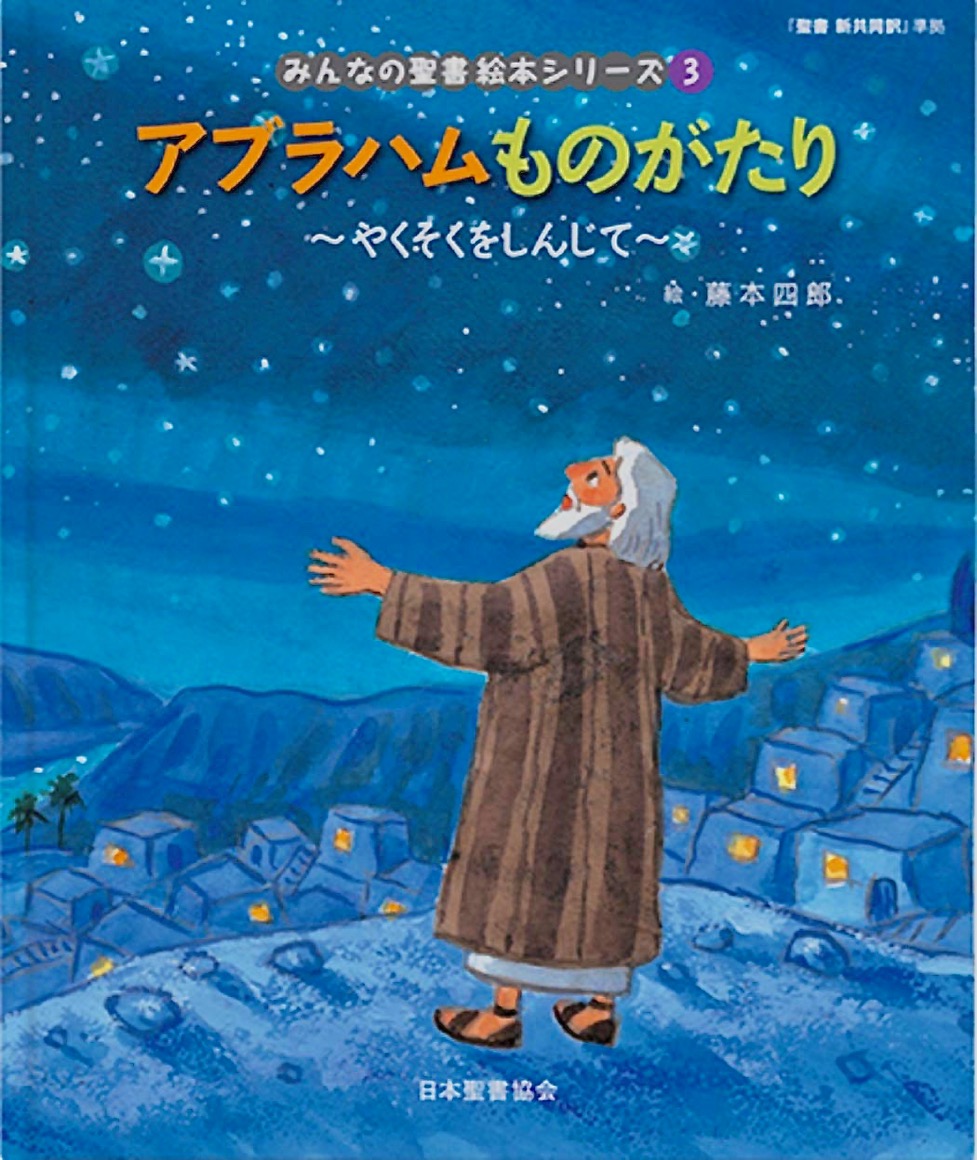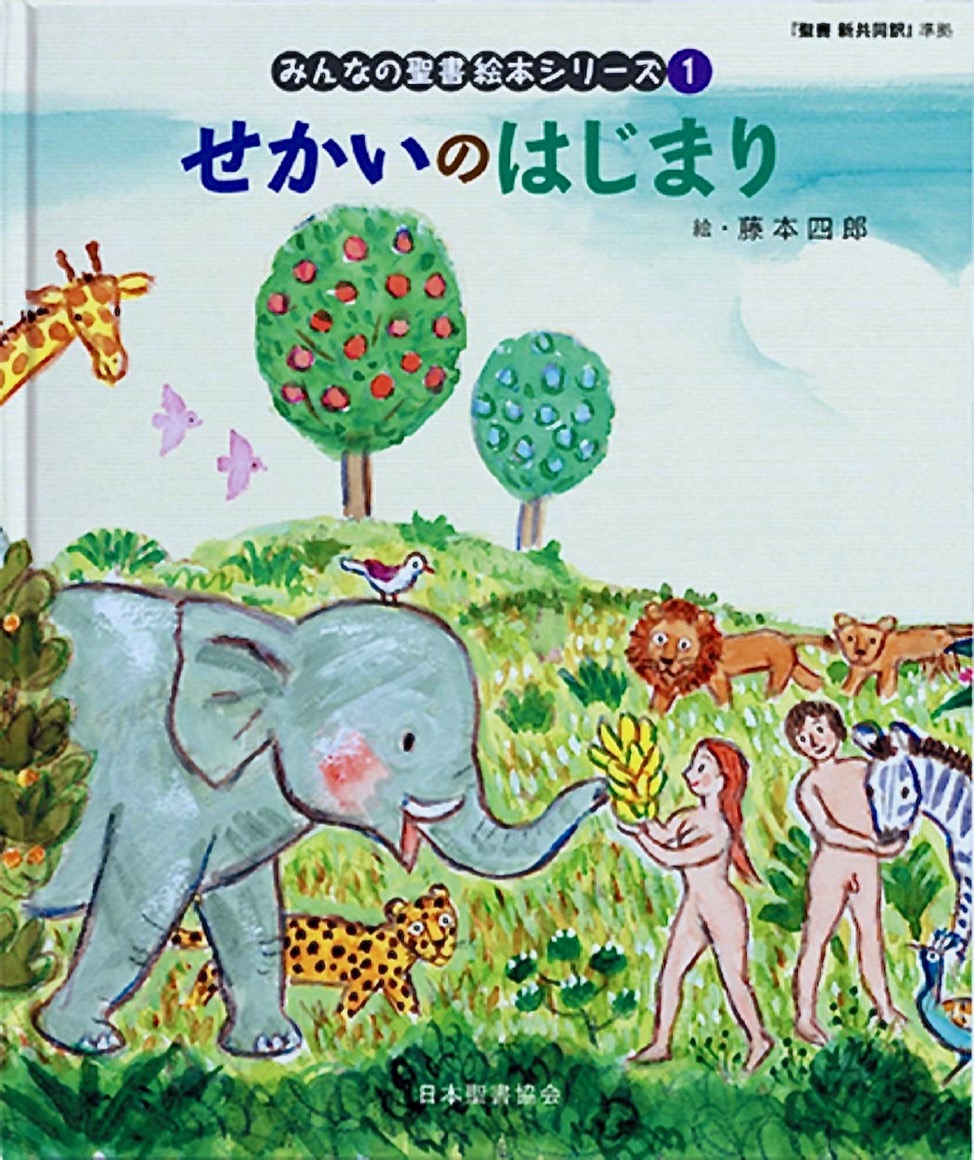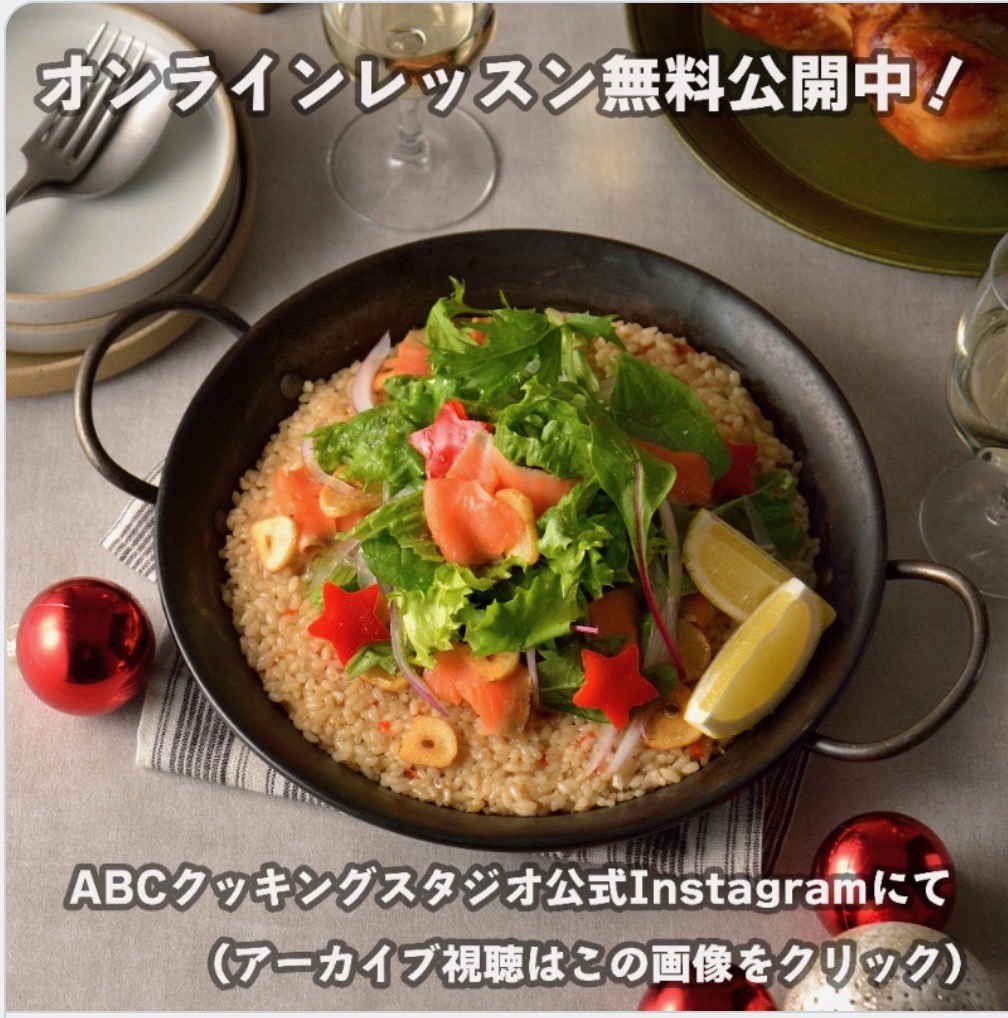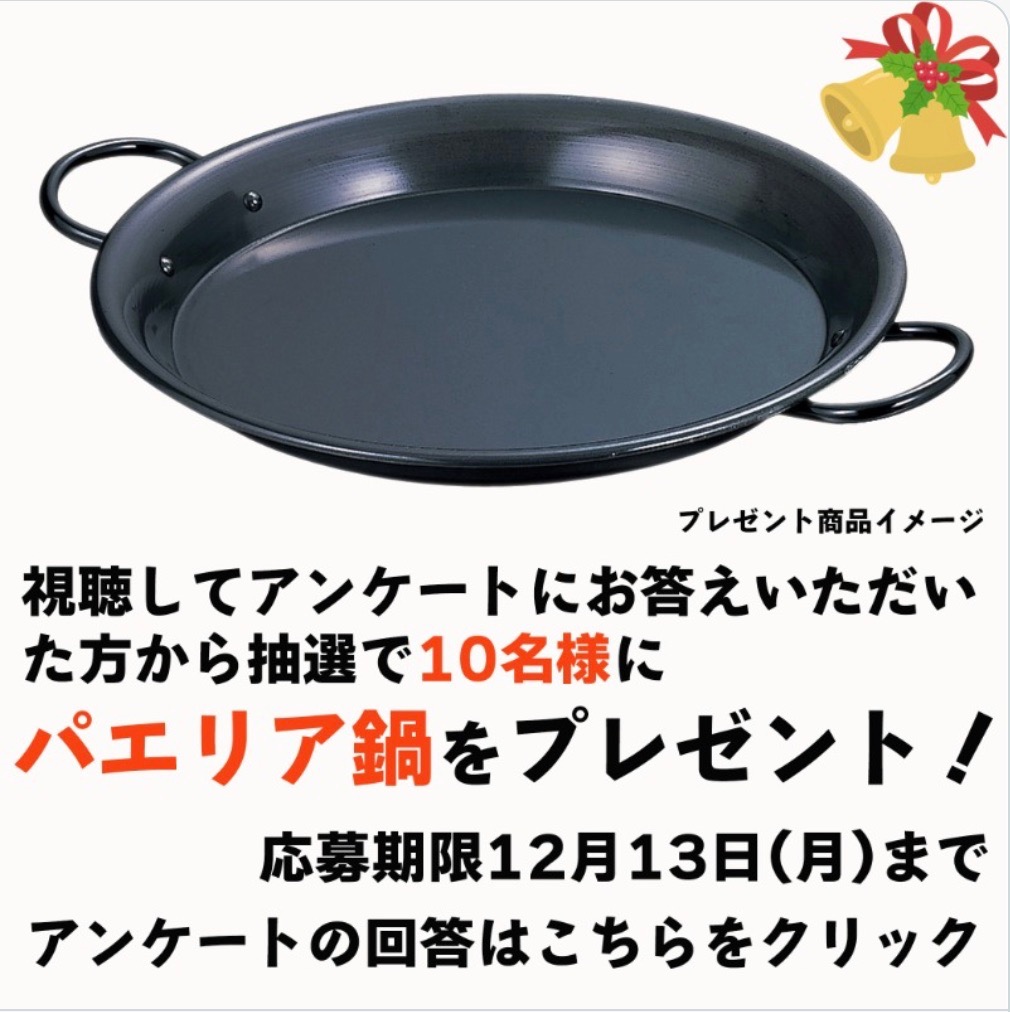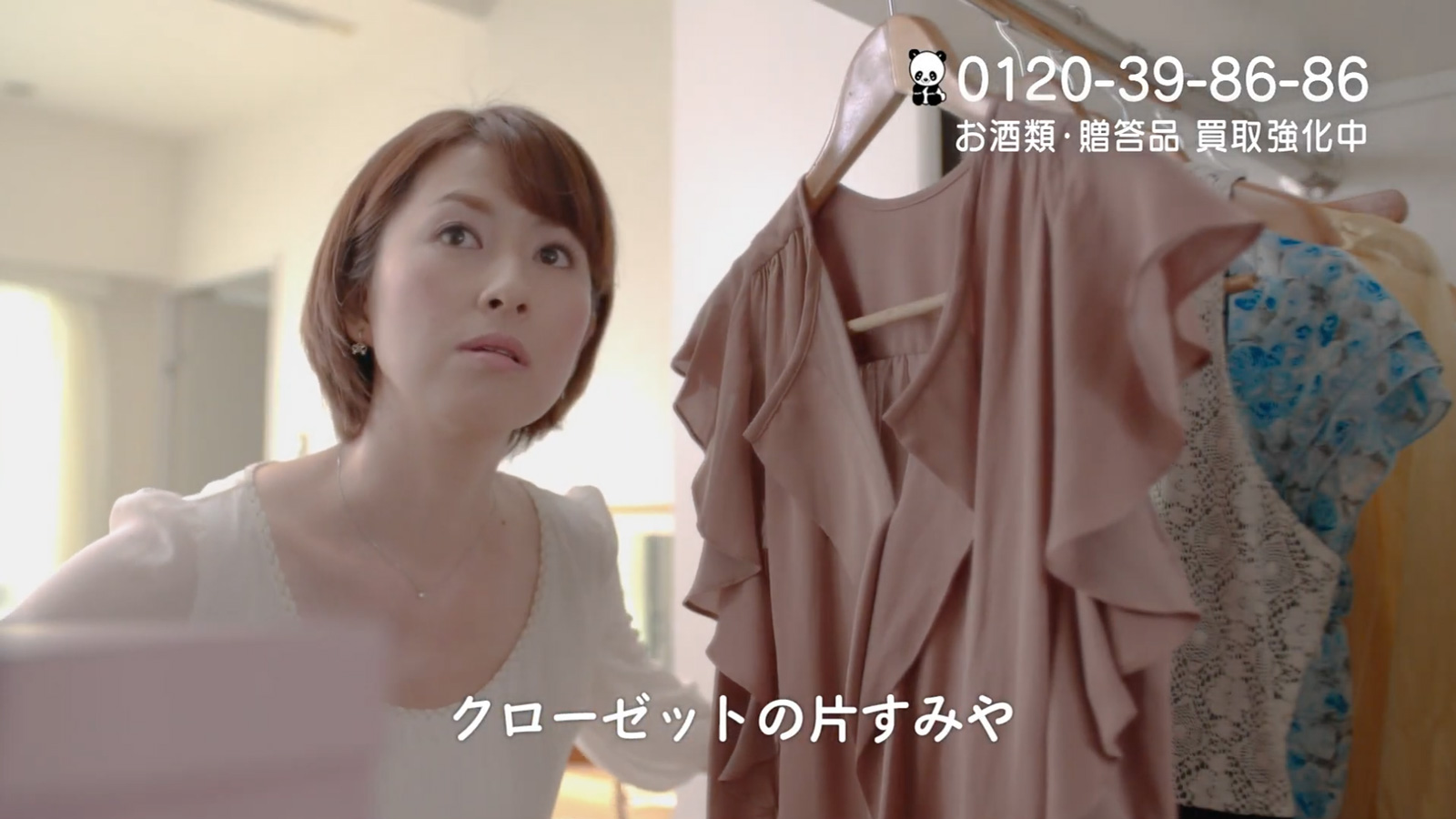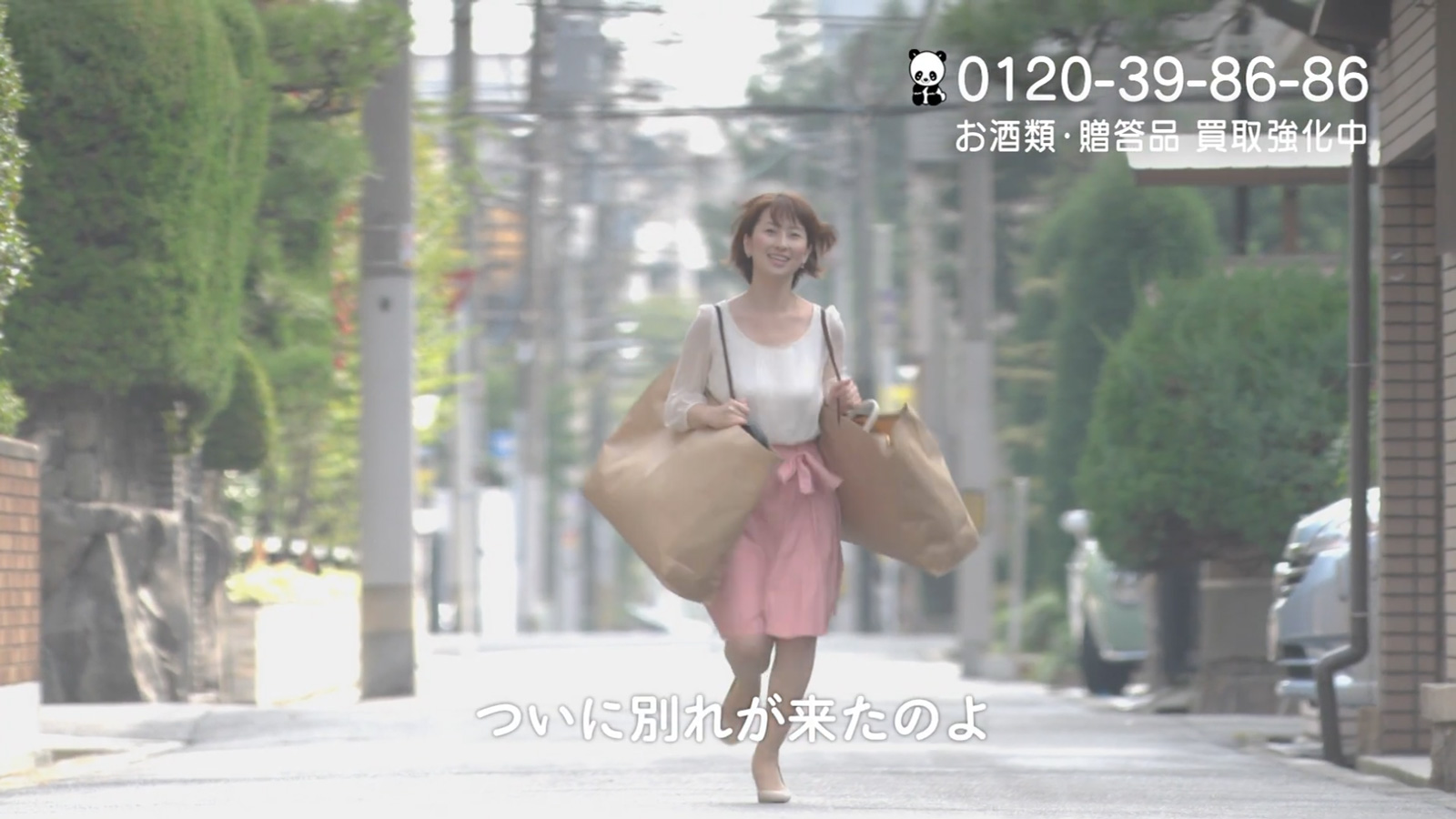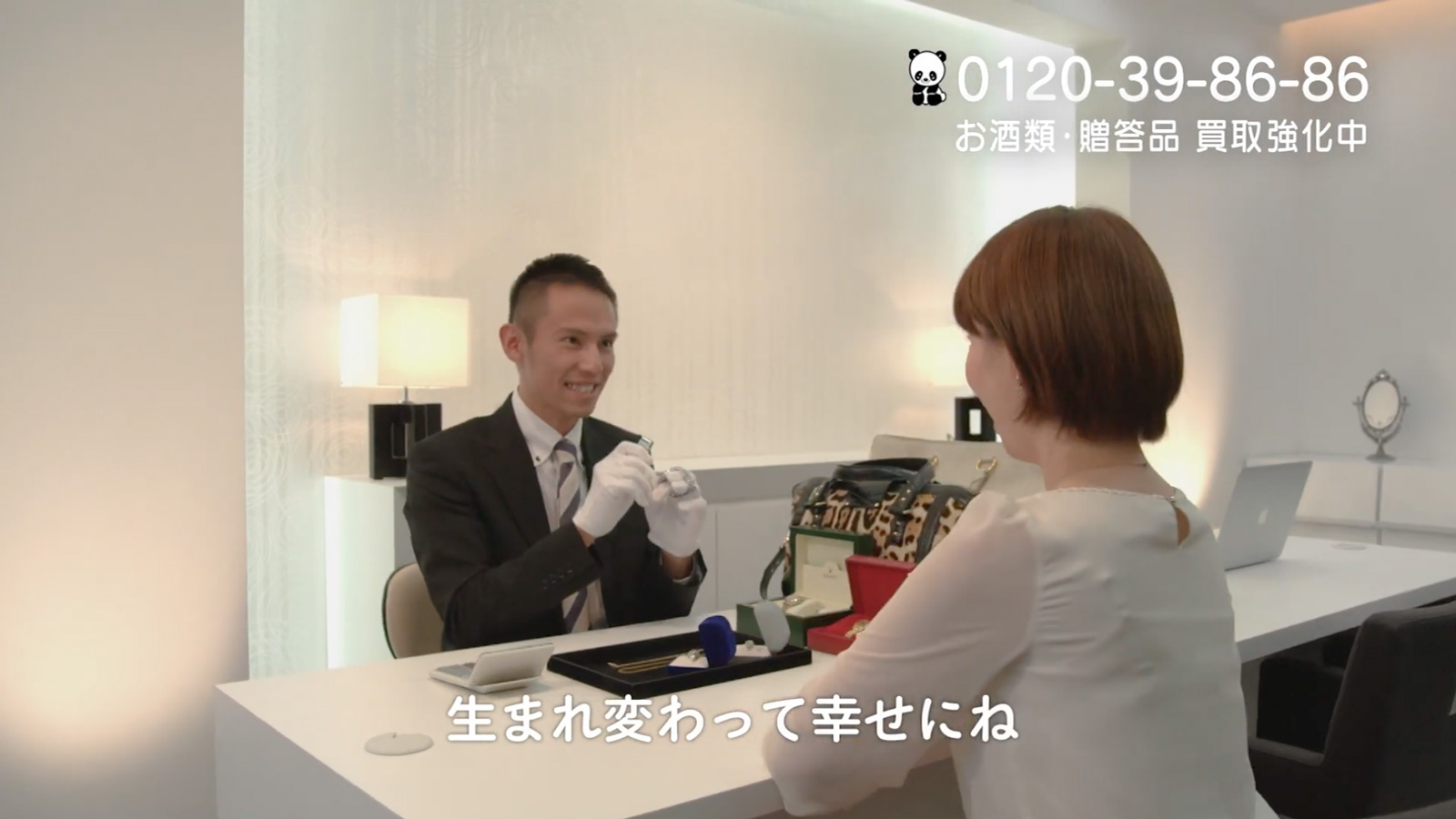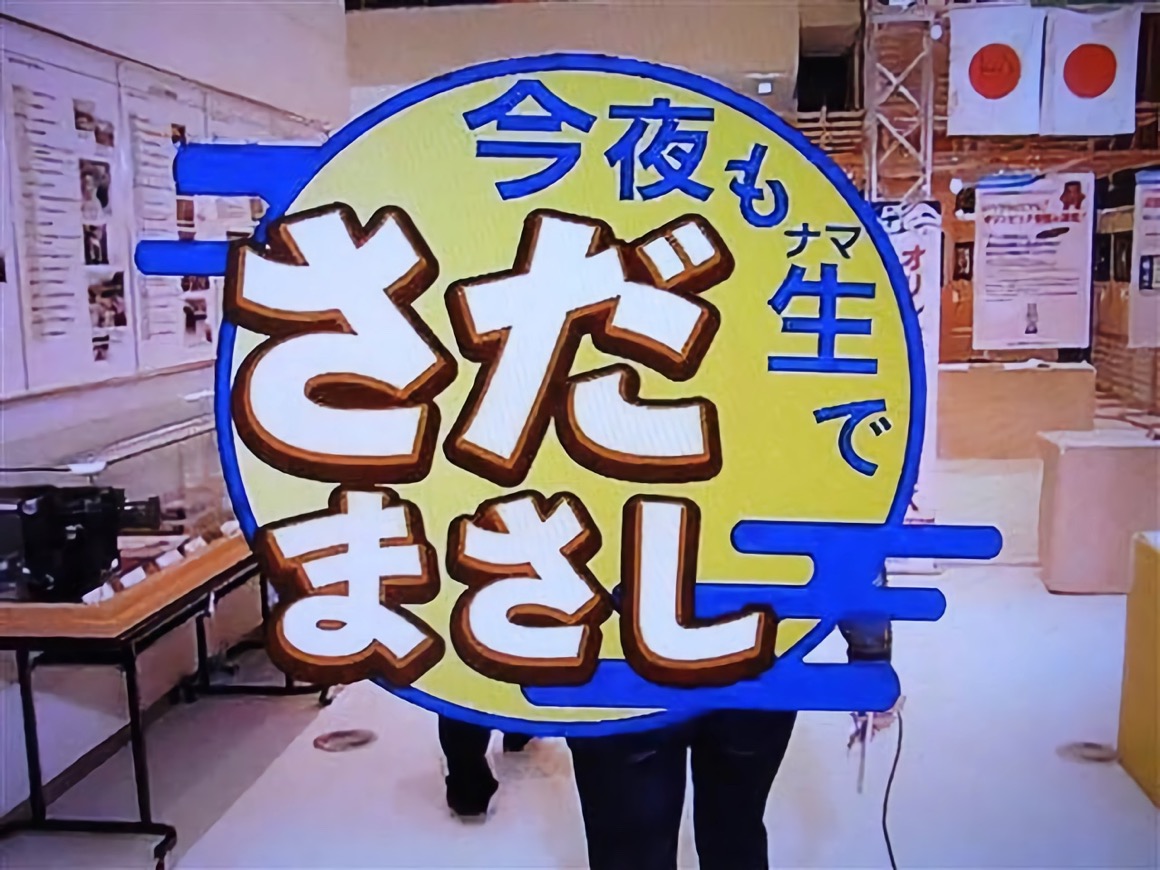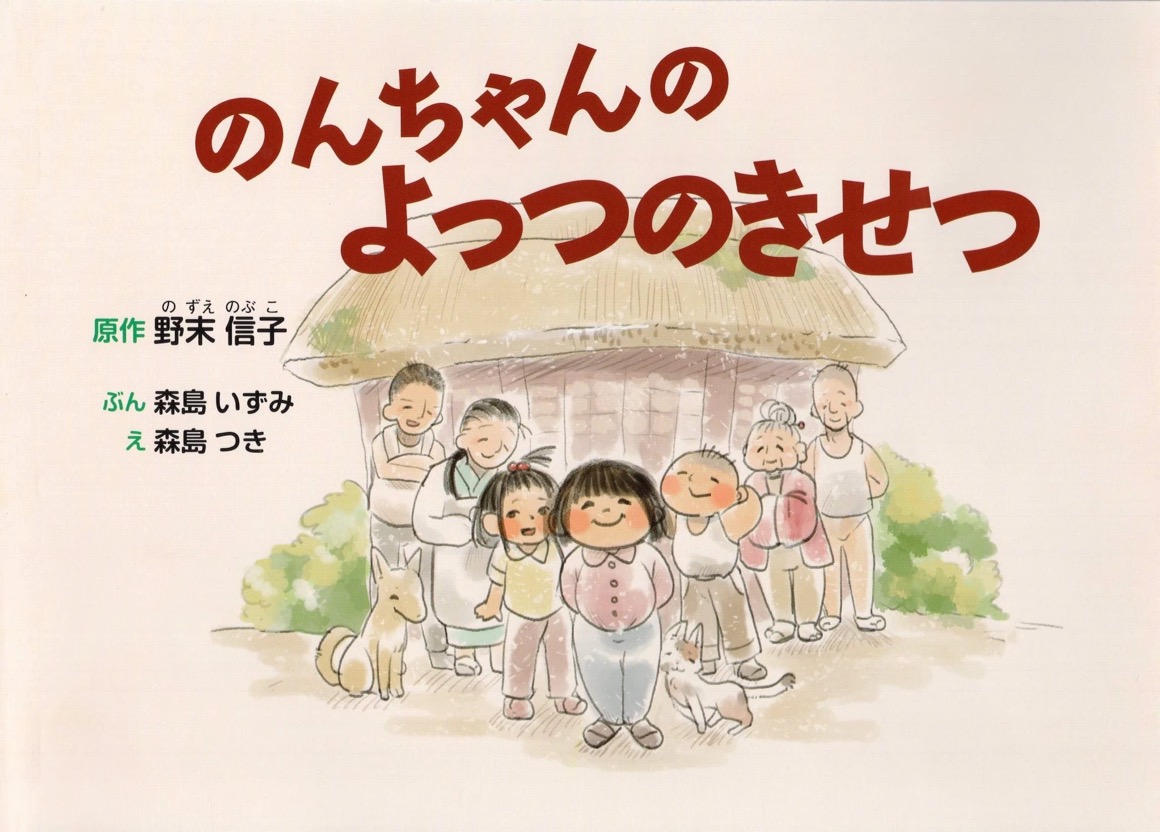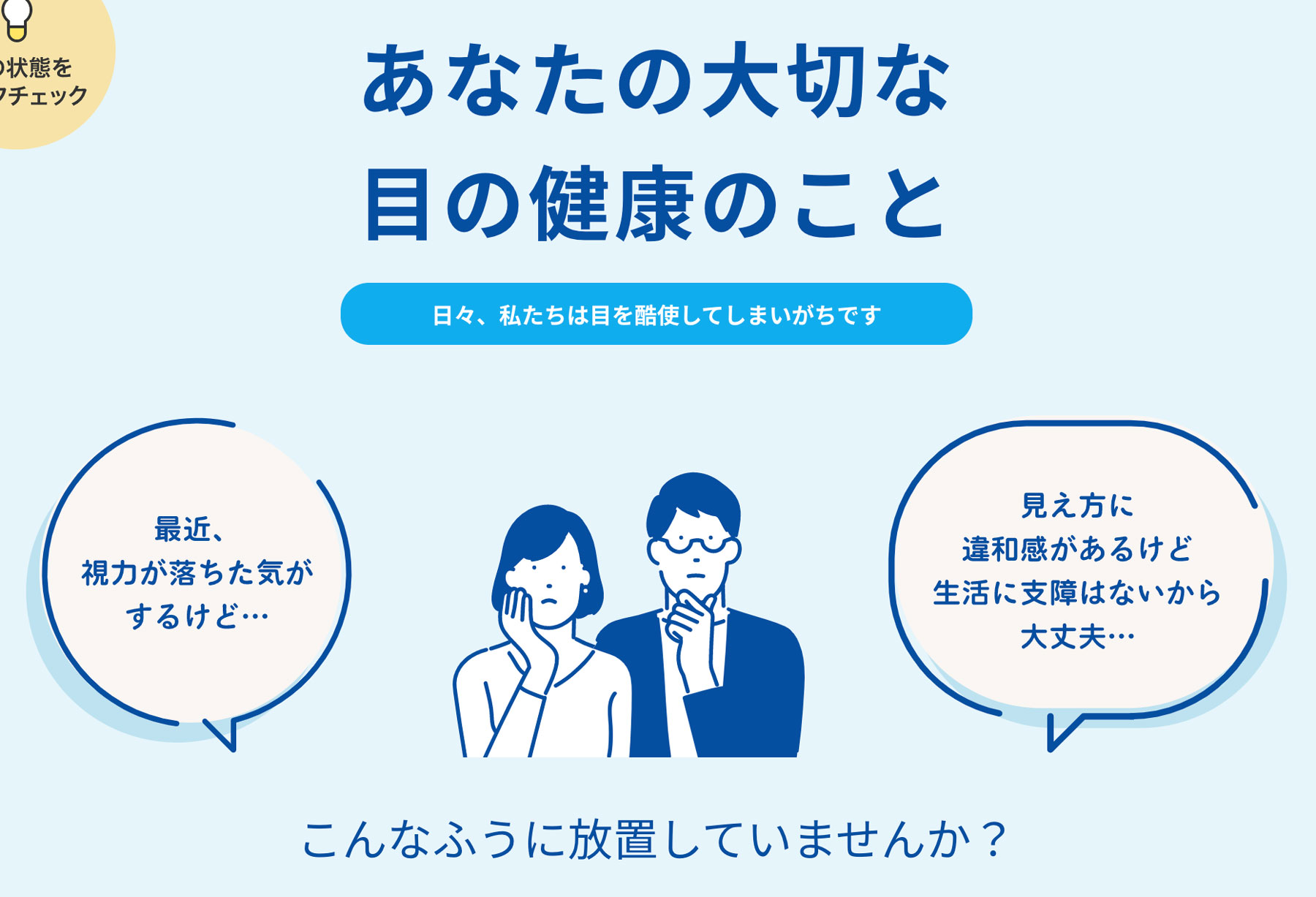
百均の商品 takumi
百均で見かけた「墨東レラ」です。
写真に写ってる文字はすべて墨東レラですが、機械的に太らせてるところがありますね…。
英会話の本の表紙 takumi
書名:NHKラジオ 英会話タイムトライアル 2024年4月号
発行:NHK出版
「タイムトライアル」と、その下の「スピーキング力の〜トレーニング」も墨東フォントですね。
ざっくり調べてみたところ、2024年3月号までは他社フォントを使っていたようですが、4月号から墨東を採用するようになったようです。
本の表紙 さとうゆたか
書名:吉本興業女マネージャー奮戦記「そんなアホな!」
著者:大谷由里子
発行:立東舎文庫
広告画像 さとうゆたか
墨東ルイカのようだ。
AdobeFontsを使ったかな…。
広告画像 さとうゆたか
JR東日本の広告。
広告画像 さとうゆたか
アイス de ヤクルト
この書体は、墨東レラ。
イオン えらぼうフェア takumi
「イオン えらぼうフェア 2024」の動画内で「墨東レラ」が使われていました。
墨東レラ-6のようですね(これは太らせてるかも)。
テレビCM さとうゆたか
墨東ルイカです。
熱血!SUUMO学園
もうひとつ。
イベントロゴ さとうゆたか
墨東ルイカですね。
あだち生きもの図鑑をつくろう!2024春編
〔4月1日〜5月12日開催〕
アドビフォントで さとうゆたか
数日前から、みぞれ墨東フォントがAdobeFontsで使えるようになりました。